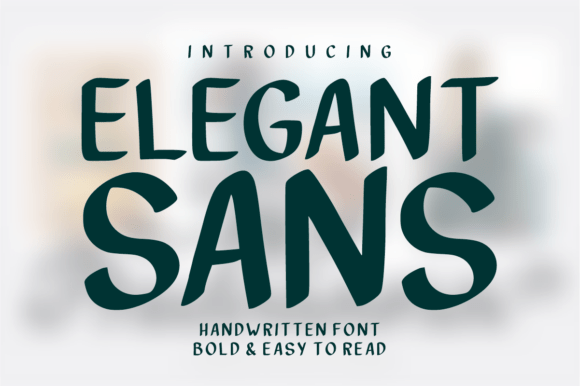
Elegant Sans
Het vinden van de juiste ontwerpelementen kan lastig zijn, maar Elegant Sans biedt een uitzonderlijke collectie die uw werk direct naar een hoger niveau tilt.
Of u nu POD-producten (Print on Demand), huwelijksuitnodigingen of afbeeldingen voor sociale media maakt, Elegant Sans is een ideale keuze.